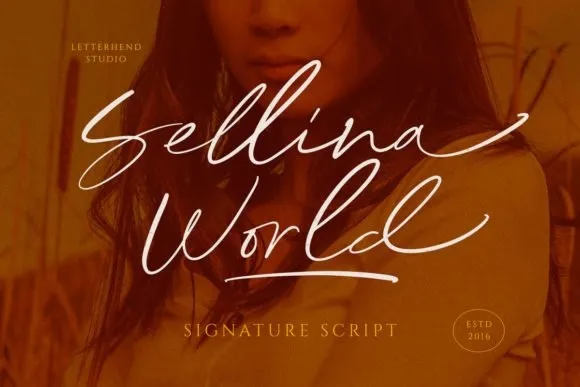
A ‘Sellina Word Font’ é uma elegante tipografia script feita para quem busca estilo singular e versatilidade em seus projetos digitais. Com suas linhas finas e arredondadas, essa fonte é uma verdadeira obra-prima, especialmente adaptada para trabalhos que exigem um toque mais suave no design editorial ou nas redes sociais. Suas letras distintas e bem equilibradas tornam-a perfeita para quem busca criar designs impressionantes e diferentes. Se você está à procura de uma fonte que pode transformar qualquer projeto em algo único, a ‘Sellina Word Font’ é sua escolha ideal. Não importa se você está criando um layout editorial sofisticado ou simplesmente deseja dar um toque especial a suas postagens nas redes sociais, essa fonte oferece o estilo e versatilidade necessários para alcançar seus objetivos de design.